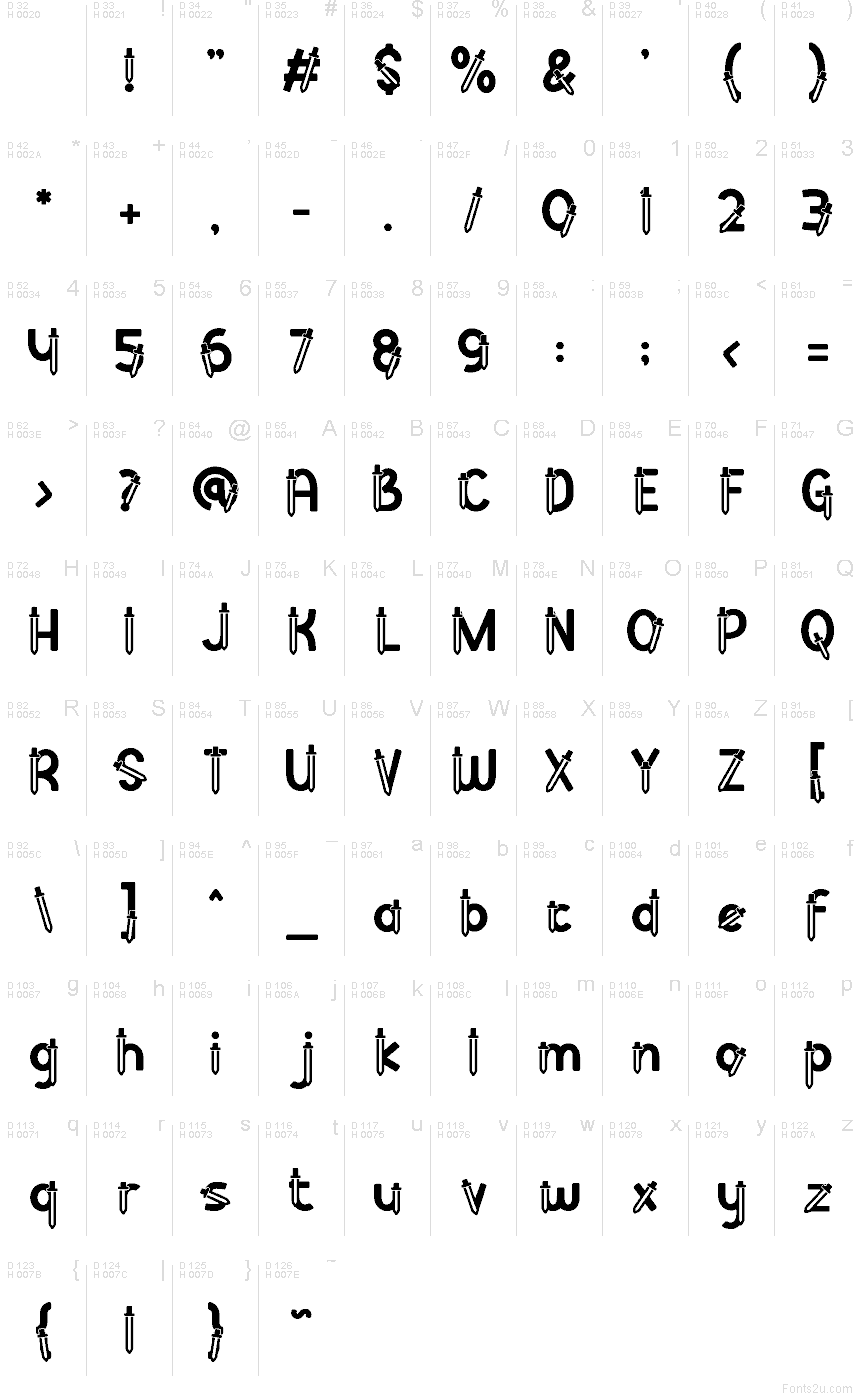
Clever Science Pipet
Clever Science Pipet, eine kostenlose, wissenschaftlich inspirierte Display-Schrift von Putracetol Studio, kombiniert kräftige, schwarze Buchstaben mit Pipetten-Silhouetten für einen verspielten Labor-Look. Das Alphabet wirkt wie um das wiederkehrende Tropfen-Motiv herum konstruiert, wobei abgerundete, kompakte Formen durch spitze Kappen und präzise Kanten unterbrochen werden, die an einfache Laborausrüstung erinnern.
Die Schrift eignet sich hervorragend für Plakate zu Kinderworkshops, STEM-Club-Branding, Klassenzimmer-Aushänge, Verpackungen für Experimentierkästen oder für Bildungs-Zines, bei denen ein thematisch passender kostenloser Font schnell die gewünschte Botschaft vermittelt. Da die Buchstaben selbst das Pipetten-Konzept in sich tragen, funktioniert sie auch wunderbar für kurze Logotexte, Titelkarten und Initialen, die ohne zusätzliche Illustration ein sofort erkennbares Labor-Flair benötigen.